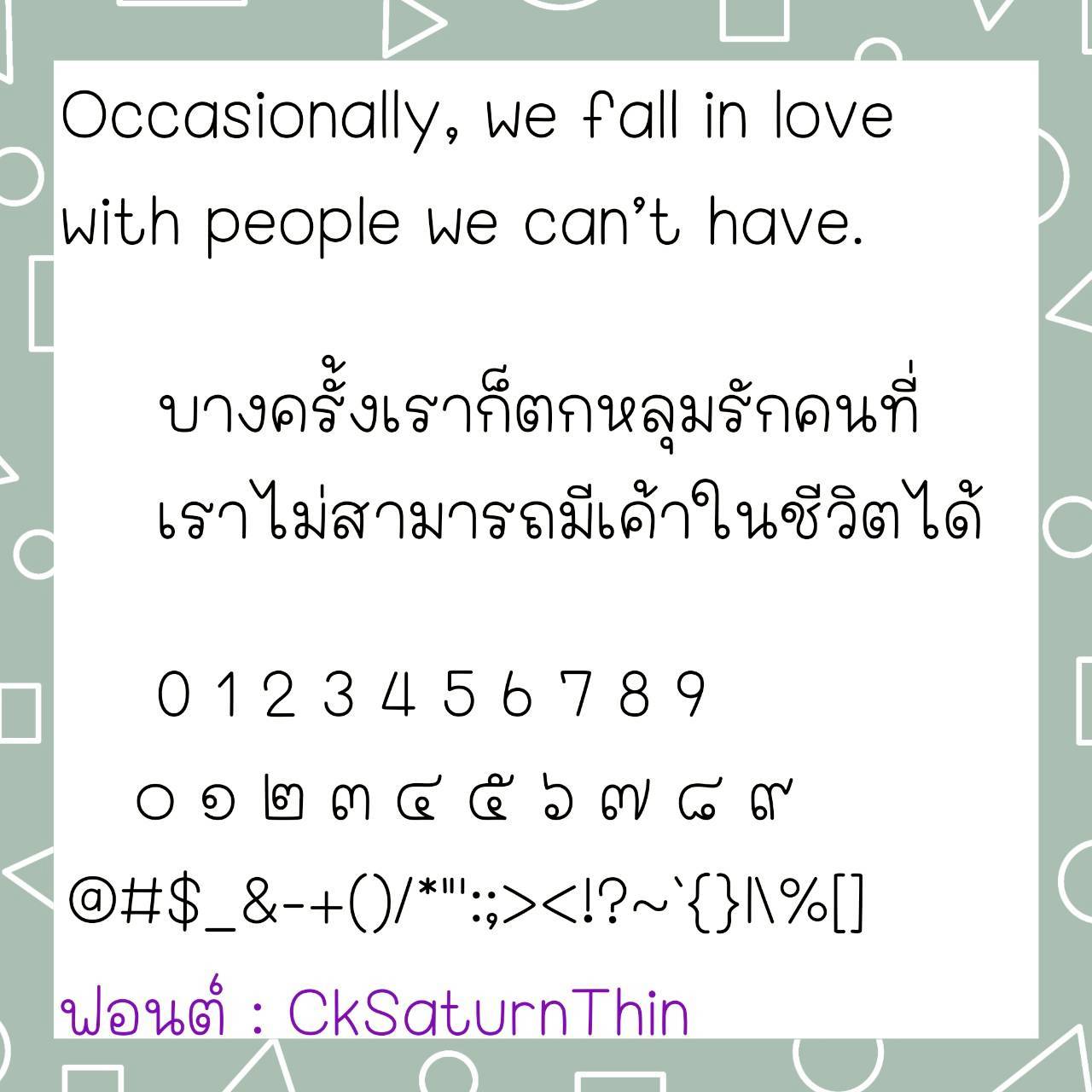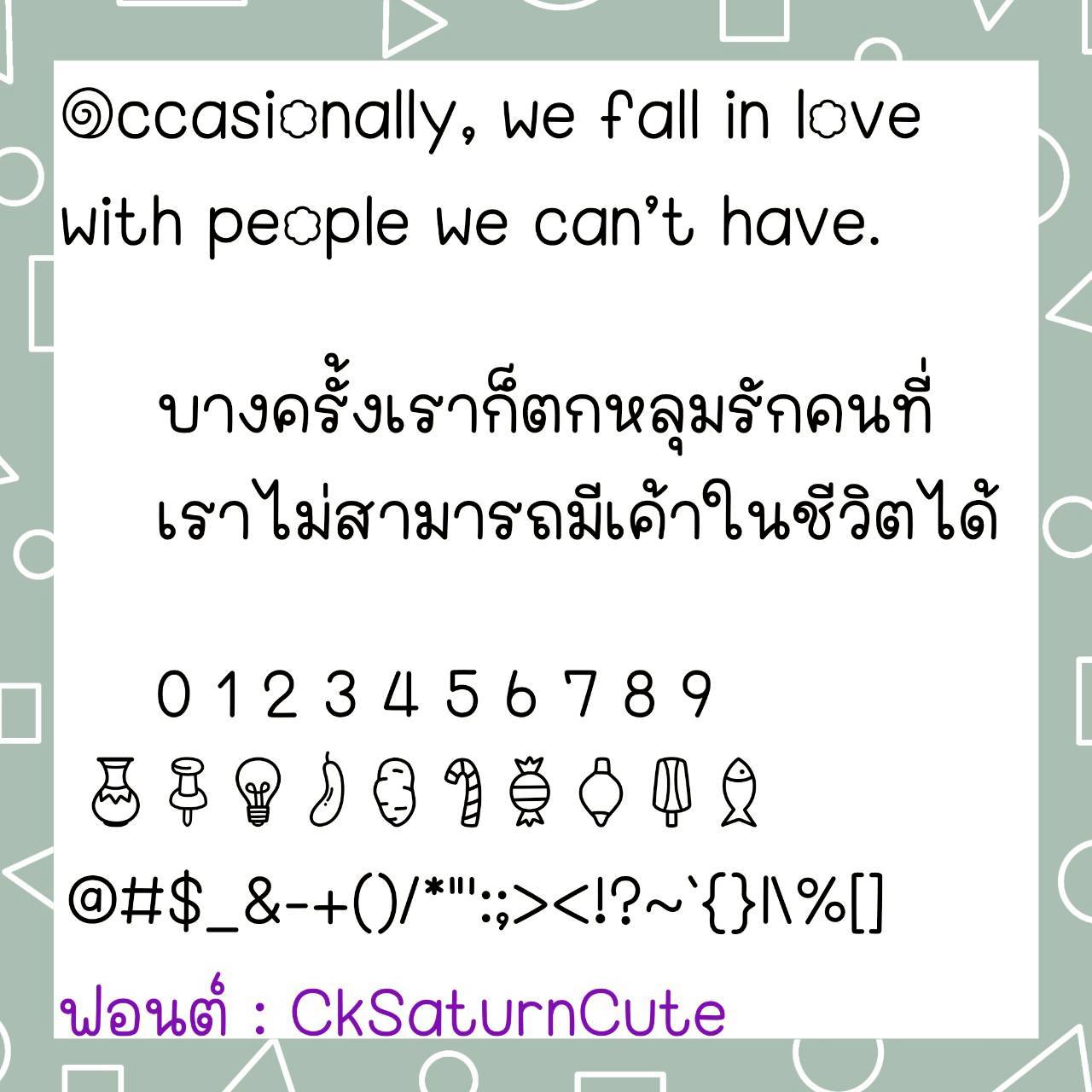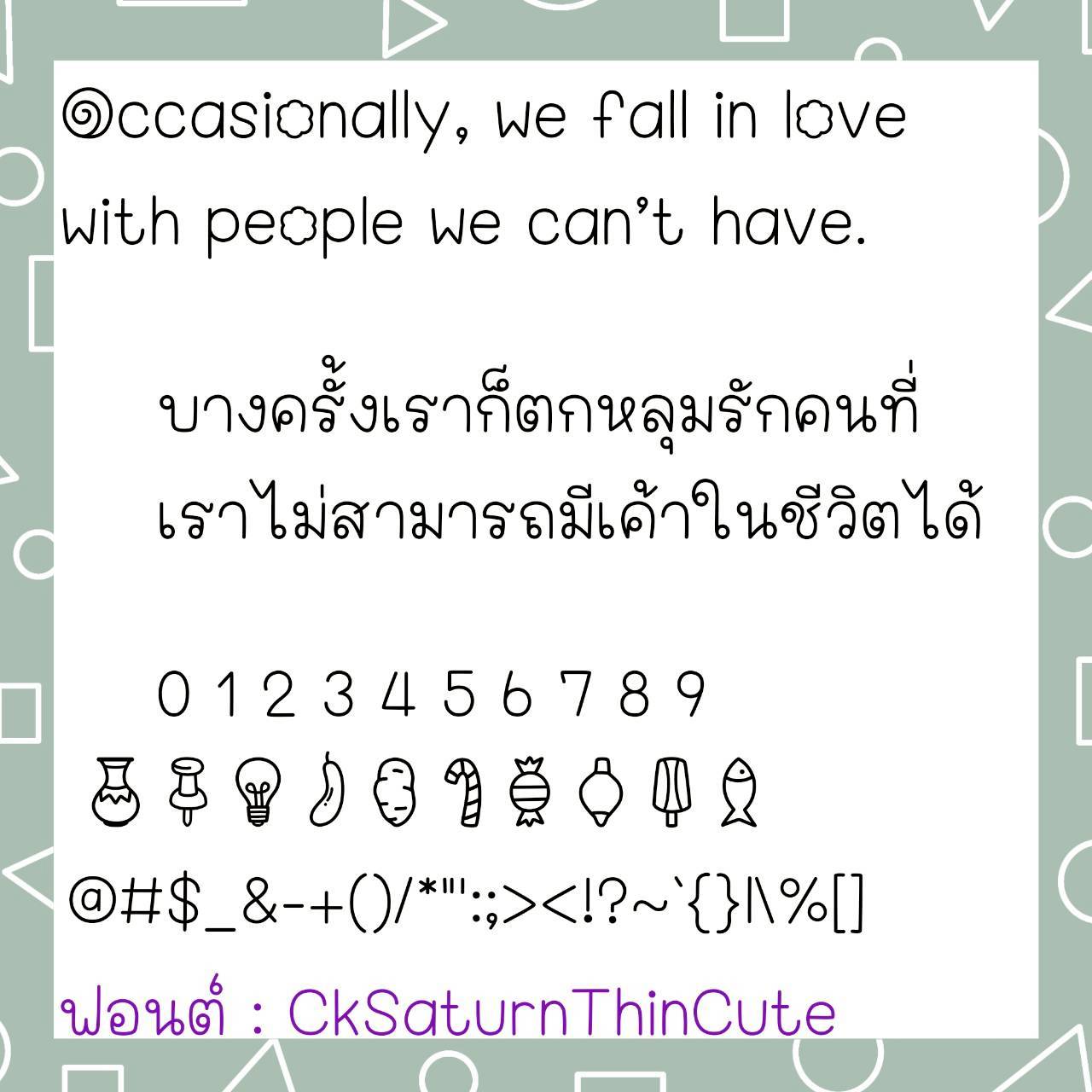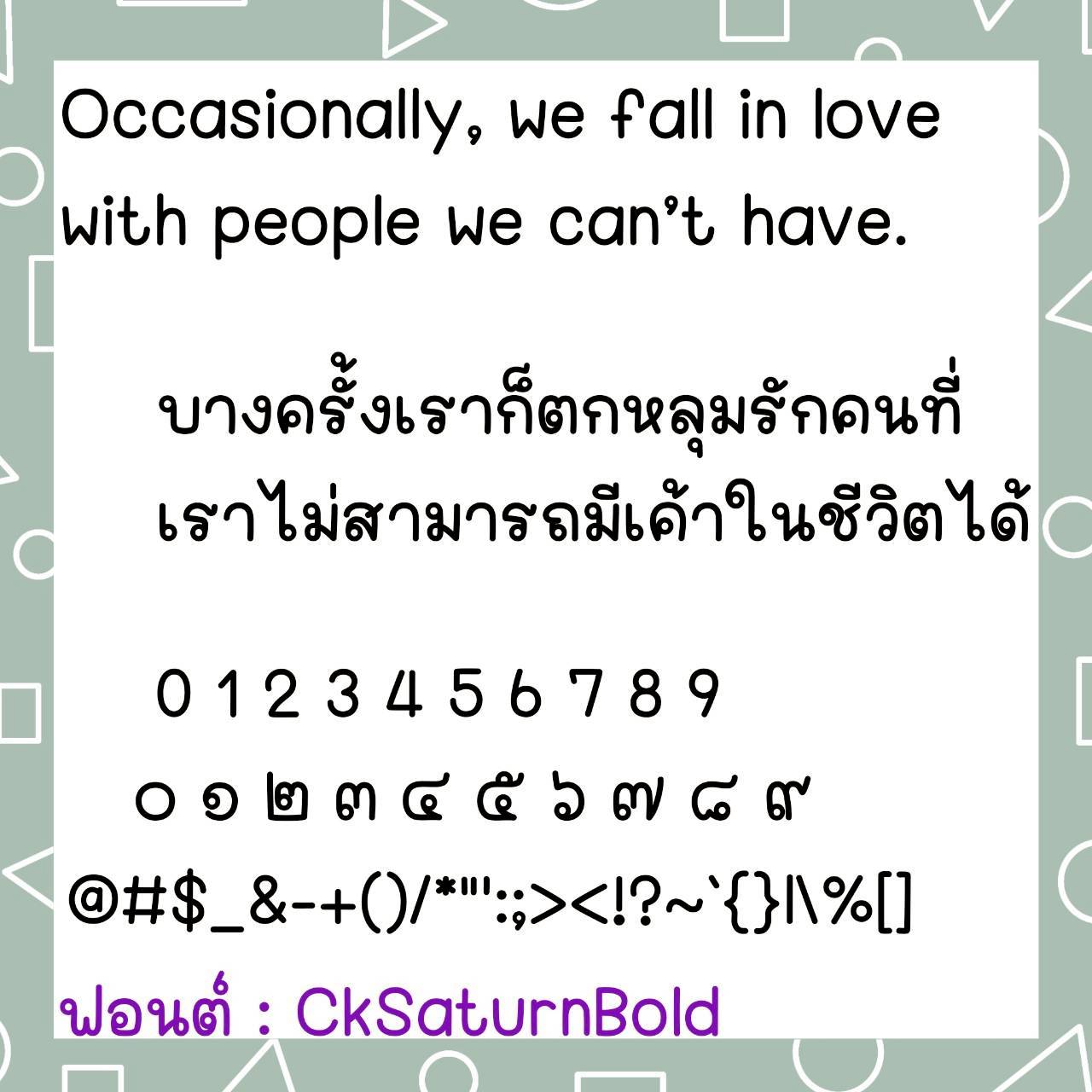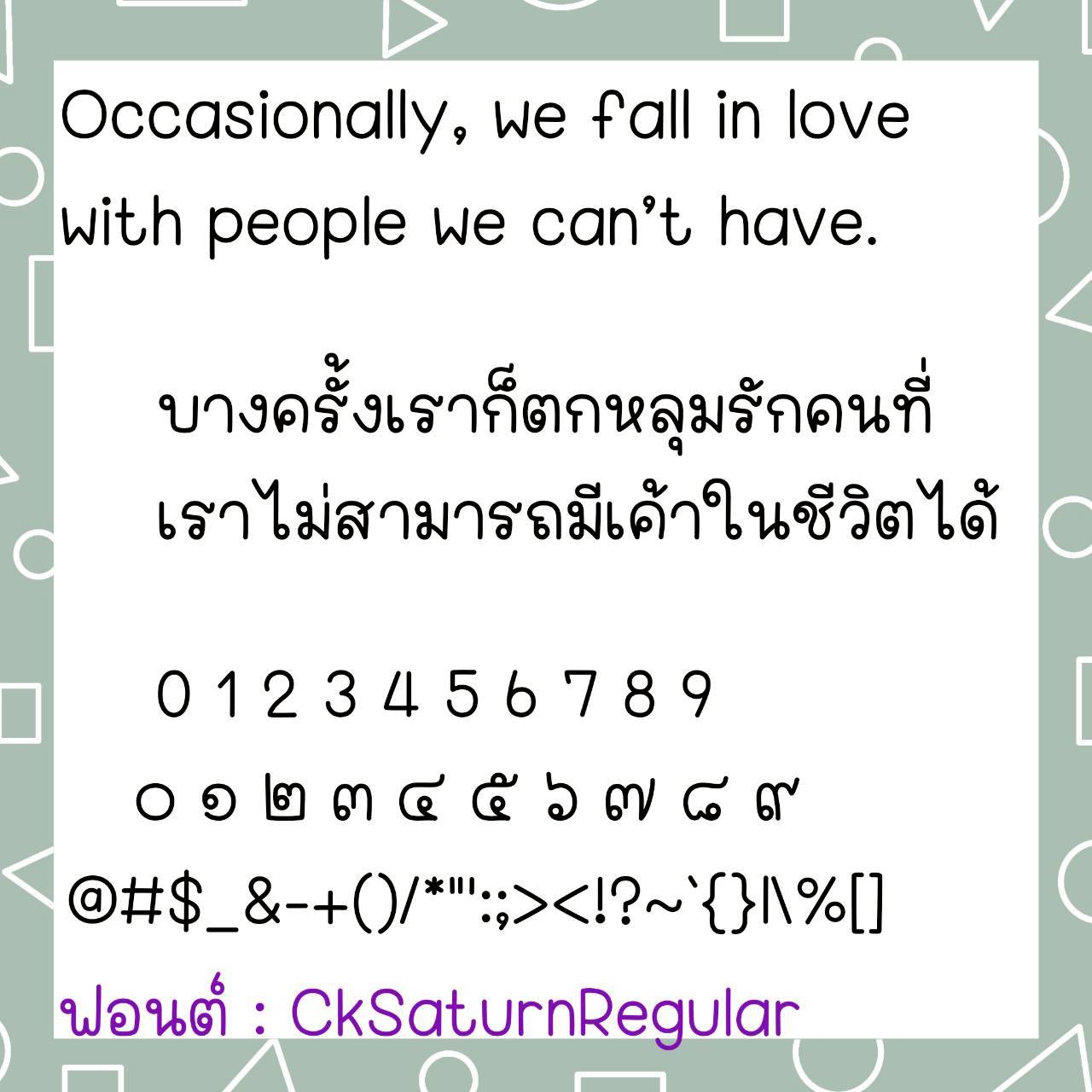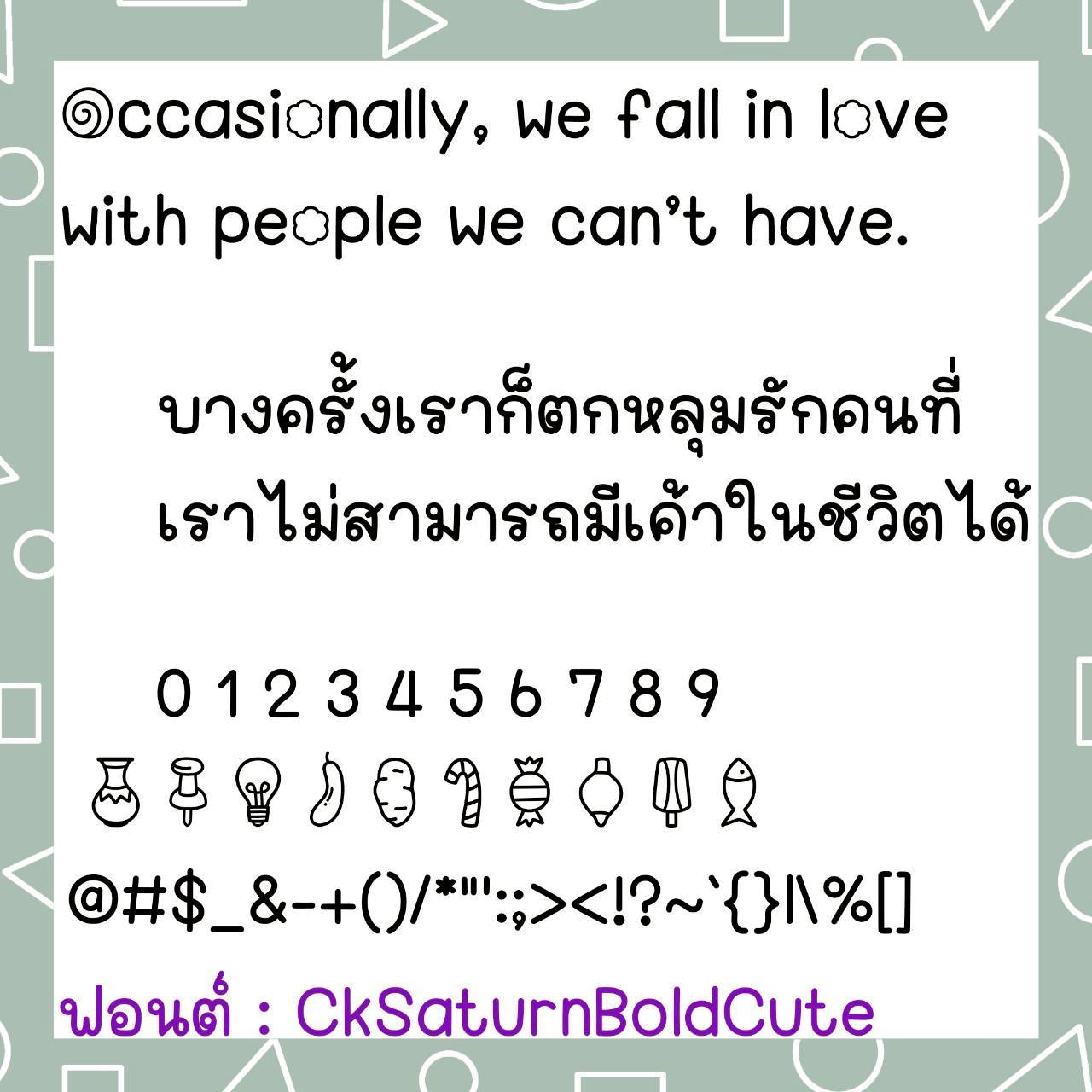
Font CkSaturn
ชื่อสินค้า : Font CkSaturn 💙
🔸 ฟอนต์ลายมือแนวอวบอ้วน ตัวกลมมน ดูน่ารักเรียบร้อย อ่ายง่ายมากๆ และยังมีไฟล์อิโมจิน่ารักๆที่ใช้แทนเลขไทยให้ด้วยค่ะ 🥰💙
🔹 This handwritten font has a chubby, rounded style, making it cute, neat, and very easy to read. It also includes cute emoji files that can be used to replace Thai numerals. 🥰💙